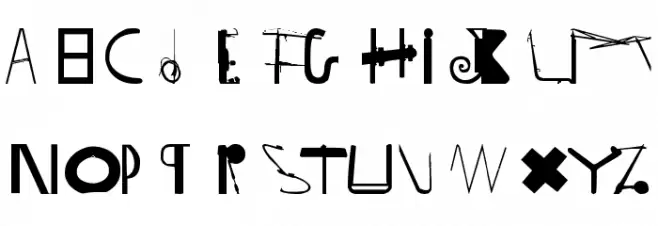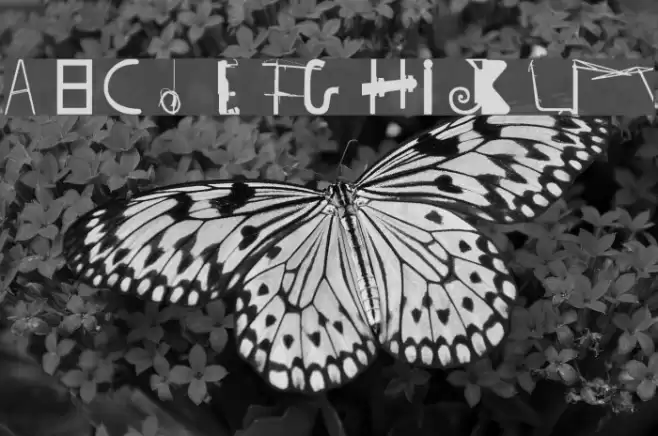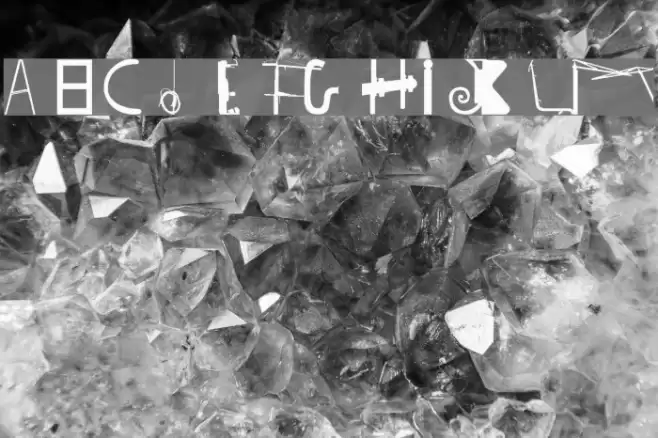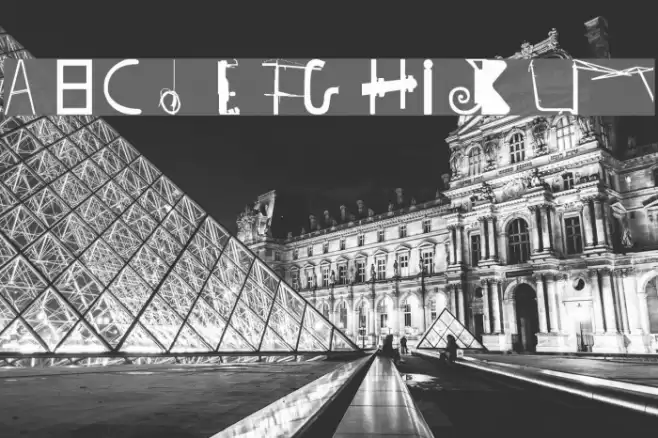
funQuandary Font
| 全体的なスタイル | Artistic, Whimsical, Creative |
| 用途 | Logos, Posters, Artistic Branding |
| おすすめプロジェクト | Ideal for creative projects such as posters, album covers, artistic branding, and any design work that seeks to stand out with a unique and unconventional style. |